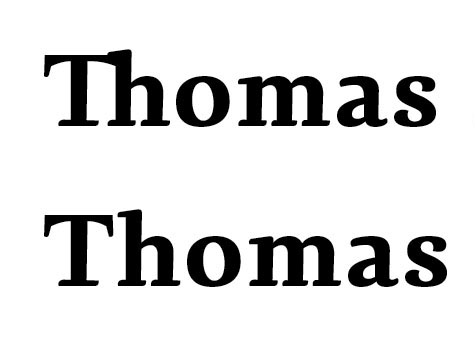
Th-Ligatur oder nicht?
Die Dederon Serif bietet eine Th-Ligatur an. Ich weiß aber ehrlich gesagt nicht ob ich sie verwenden möchte.
Das Ergebnis wirkt auf mich eher wie ein Fehler ... Was meint ihr?
Wie darf ich das deuten? Bist du für oder gegen die Verwendung der Ligatur?
Es geht übrigens wirklich um diesen Namen (auf Briefbogen und Visitenkarte).
… aber so was hier könnte doch gehen …
Na ja, da wirkt das h wieder etwas kastriert, und ich vermute mal, innerhalb einer Zeile mit weiteren Buchstaben mit Oberlänge wird das noch mehr auffallen. Von den »verschiedenen Möglichkeiten« die Ralf erwähnt hat, fällt mir gerade keine ein. Ein Th-Verbund ist schon etwas problematisch.
Ich würde die Buchstaben eher einen Hauch trennen, als sie zu verbinden: den Querbalken des T eine Idee schmaler, die obere h-Serife ein bisschen kürzer, damit die beiden entspannt nebeneinander stehen. Gerade bei dieser Schrift, bei der die Oberlänge des h höher hinaufreicht als das T finde ich eine ansprechende Verbindung der beiden schwierig.
Na ja, da wirkt das h wieder etwas kastriert, und ich vermute mal, innerhalb einer Zeile mit weiteren Buchstaben mit Oberlänge wird das noch mehr auffallen.
da ist was dran. dann vielleicht so, inspiriert von verschiedenen adobe-schriften:
… dann vielleicht so …
Irgendwie sucht mein Auge da die ganze Zeit nach der Serife. Aber ich sehe auch keine Möglichkeit, sie unterzubringen. Wirklich heikel, die Sache.
für mich funktioniert sowas hier:
(wobei hier zwar verbunden wurde, aber der Abstand dann trotzdem noch zu weit ist ...)
oder auch das da (nur die obere Zeile ist hier natürlich relevant)
(in Kursiven scheint das generell besser zu funkionieren).
Also: die Serife des h muss zumindest durch ein "hochziehen" des T-Querbalkens angedeutet sein.
Ob man eine Th-Ligatur braucht? Man sollte zumindest drüber nachdenken, bevor man es einbaut, nur damit man es hat ...
Als Schriftgestalter kann man da auch gut mit einer kontextsensitiven T-Alternative (mit einem so weit gekürzten T-Balken, dass dieser "richtig" lang aussieht) gegensteuern. In der Tierra Nueva Sur (das Script-Ding) habe ich z.B. den T-Balken vor Oberlängen-Folgezeichen z.B. anders ausgeführt, sodass dieser das Folgezeichen an einer schöneren Stelle kreuzt.
Dein Vorschlag ist ein sehr schöner Weg, Sebastian. Und der rechte T-Querbalken ist durch die Beschwerung mit zusätzlicher Form und Farbe in allen Ligatur-Beispielen (ausser dem kursiven), optisch deutlich länger.
offene Türen eingerannt …
Nur zur Klarstellung:
Die beiden Beispiele sind nicht von mir (ach könnt ich wieder mal einen Font-Editor öffnen ...), ich hab sie nur gefunden und verlinkt um zu zeigen wie so eine Th-Verbindung meiner Meinung nach am besten funktioniert.
Und wie Norbert schreibt: Die Länge des rechten T-Arms müsste da natürlich noch angepasst (gekürzt) werden ... einerseits, weil er optisch über das h hin tatsächlich verlängert wird, andererseits weil der Binnenraum zwischen T und h durch die Verbindung enger umschlossen wird, und Flächen die enger umschlossen sind größer wirken als die selben mit weniger definierter "Umrahmung".